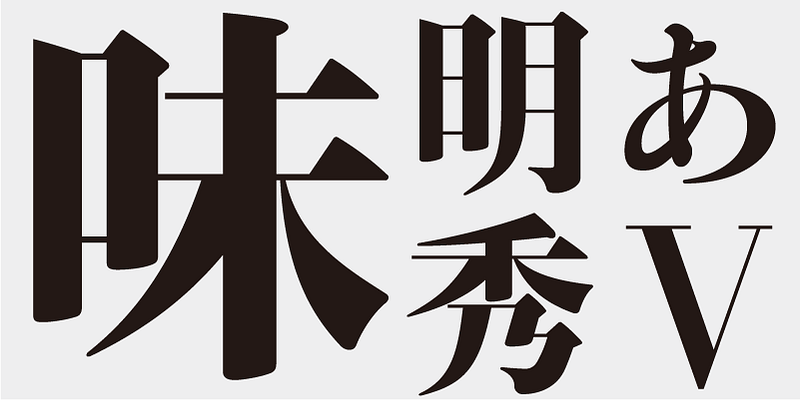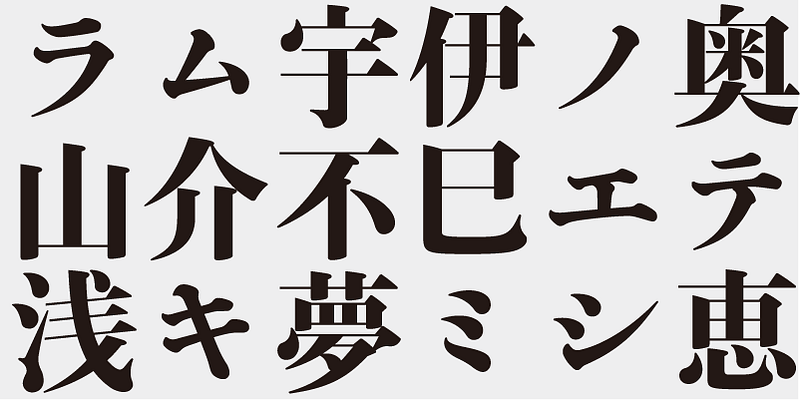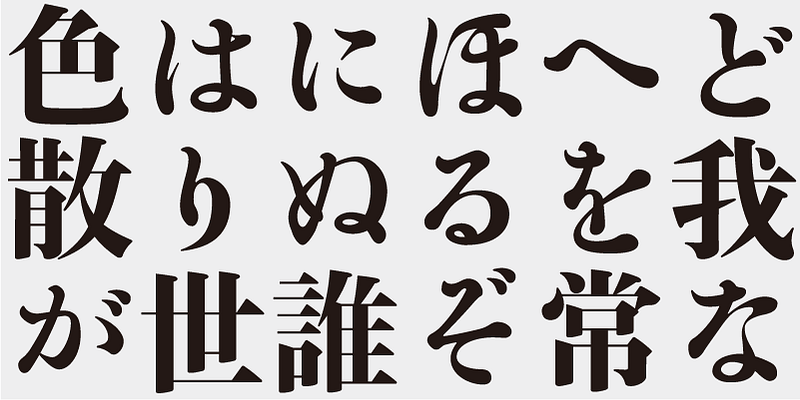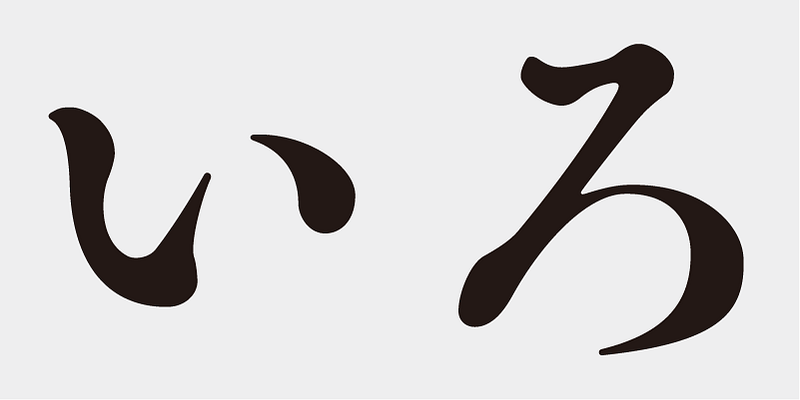
Aunque Ajimin tiene el sabor de los tipos de metal caliente, no pretende ser un revival, sino un nuevo tipo de letra para cartelería. Al igual que Bodoni, sus trazos verticales son claros y gruesos y sus trazos horizontales son precisos y finos. Sus elementos poseen fuerza y estabilidad.
Los elementos de Ajimin Modern tienen un diseño más nítido que los de Ajimin: el inicio y el final de los trazos verticales están rebajados para aumentar la nitidez, y los trazos horizontales están cortados verticalmente al inicio y son más finos con una anchura uniforme. Ajimin Modern es un tipo de letra de estilo Mincho, nítido y elegante.
Este tipo de letra está diseñado para utilizarse en tamaños de letra más grandes (para carteles, por ejemplo), aunque es legible en tamaños más pequeños. A medida que aumenta el tamaño de la fuente, la elegancia de cada elemento de trazo se hace más visible.
Al igual que “Tsukiji-tai“, “Shuei-tai“ es uno de los estilos tipográficos más influyentes en la era de los tipos de metal caliente. Producido por la imprenta Shue-sha, que posteriormente se fusionó con otra imprenta para formar Dainippon Printing, una de las razones de su popularidad puede ser su idiosincrásico estilo caligráfico. Este diseño tipográfico utiliza tres estilos de kana diferentes de las muestras tipográficas de Shuei-tai.
Ajimin Modern Syu V/EB es una reedición de tipo de letra basada en ejemplos de material de impresión antiguo. Para mí, este diseño está basado en Shuei. El carácter “V“ del nombre de la fuente significa “Vintage“.
Este tipo de letra incluye los mejores 1.000 caracteres kanji elegidos a partir de tablas de frecuencia de caracteres elaboradas por empresas periodísticas, editoriales e institutos de investigación lingüística, además de 206 caracteres kana y signos de puntuación.
Ajimin tiene el sabor de los tipos de fundición y, como la Bodoni, sus trazos verticales son claros y gruesos, mientras que los horizontales son precisos y finos. Sus elementos poseen fuerza y estabilidad. Ajimin es un tipo de letra para pantalla único de estilo Mincho. Los elementos de la Ajimin Modern presentan un diseño más afilado, que se equilibra con la exuberancia y la elegancia del diseño. La característica más llamativa de Ajimin son sus 10 variaciones de kana, que abarcan desde diseños de estilo mano alzada, pasando por reinterpretaciones de diseños de la era de los tipos de fundición, hasta los kana de estilo moderno. Estas variaciones hacen que Ajimin resulte útil para una amplia gama de finalidades.